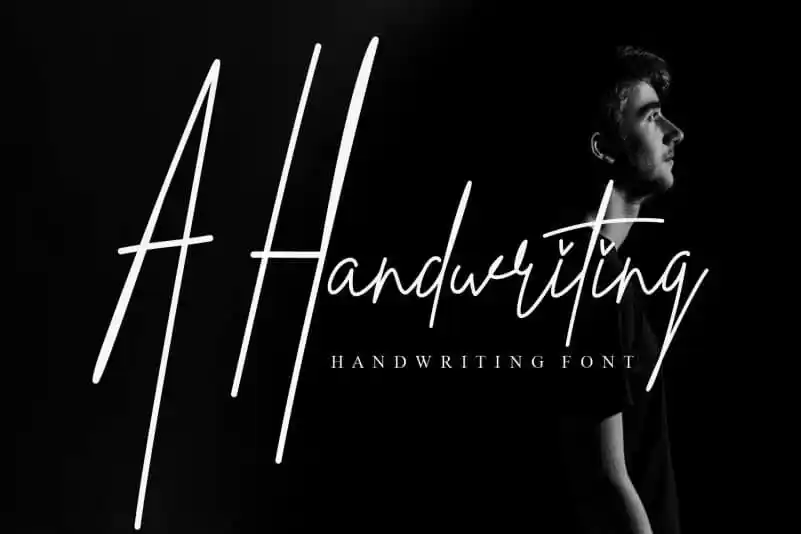
A Handwriting Script Font – Download Grátis
A Handwriting Script Font é uma nova adição à nossa ampla variedade de caracteres digitais. Este design inovador foi criado por um talentoso designer chamado creativeletter, oferecendo uma experiência única ao permitir que você expressa sua personalidade e estilo através da escrita manuscrita digital. Com suas linhas suaves e sutis, esta fonte atinge o âmago do que é essencial na escrita manual. Ela transmite confiança, simplicidade e empatia, tornando-a um recurso excepcional para designers gráficos que buscam transmitir mensagens emocionais de maneiras poderosas e únicas. Para quem está procurando por uma fonte especializada na escrita manuscrita, a Handwriting Script Font é o ideal. E se você ainda não experimentou como uma fonte em sua mão pode transformar um design simples em algo realmente impressionante, agora é a hora de testá-la para ver quão poderosa ela pode ser no seu trabalho.